Subline
In der Fachsprache von Kommunikationsagenturen und Verlagen bzw. im Fachjargon von Journalisten:innen, Texter:innen sowie Public Relations- und Werbeabteilungen von Unternehmen und Organisationen ist »Subline« ein Fachbegriff für die »Unterzeile« einer Headline (Überschrift), z.B. in Presse-, PR- oder Werbetexten; Subheadline; Subtitel; Unterüberschrift; Pl. »Sublines«.
Struktur
Die Subline (Unterzeile) steht hierarchisch unter der Headline (Überschrift) und über der Copy (Fließtext). Sie komplettiert die Headline i.d.R. als sinnstiftende Erklärung oder dient als informative Ergänzung.
Hierarchie von Headline, Subline und Copy:
1. Headline (Überschrift)
2. Subline (Unterzeile der Überschrift)
Copy (Fließtext)
Hierarchie von Headline, Subline, Dateline, Subheading und Copy:
1. Headline (Überschrift)
2. Subline (Unterzeile der Überschrift)
Dateline (Spitzmarke)
Copy (Fließtext)
( ... )
Copy (Fließtext)
3. Subheading (Zwischenüberschrift) 1)
Copy (Fließtext)
In der Typografie werden Sublines zur Strukturierung eines Schriftsatzes eingesetzt. Der Schriftgrad einer Subline ist in der Regel kleiner als die Headline und größer als die Copy. Abgesehen davon können Sublines auch in anderen Farbauszeichnung und in anderen inner- und extrafamilären Schriftschnitten ausgezeichnet werden.
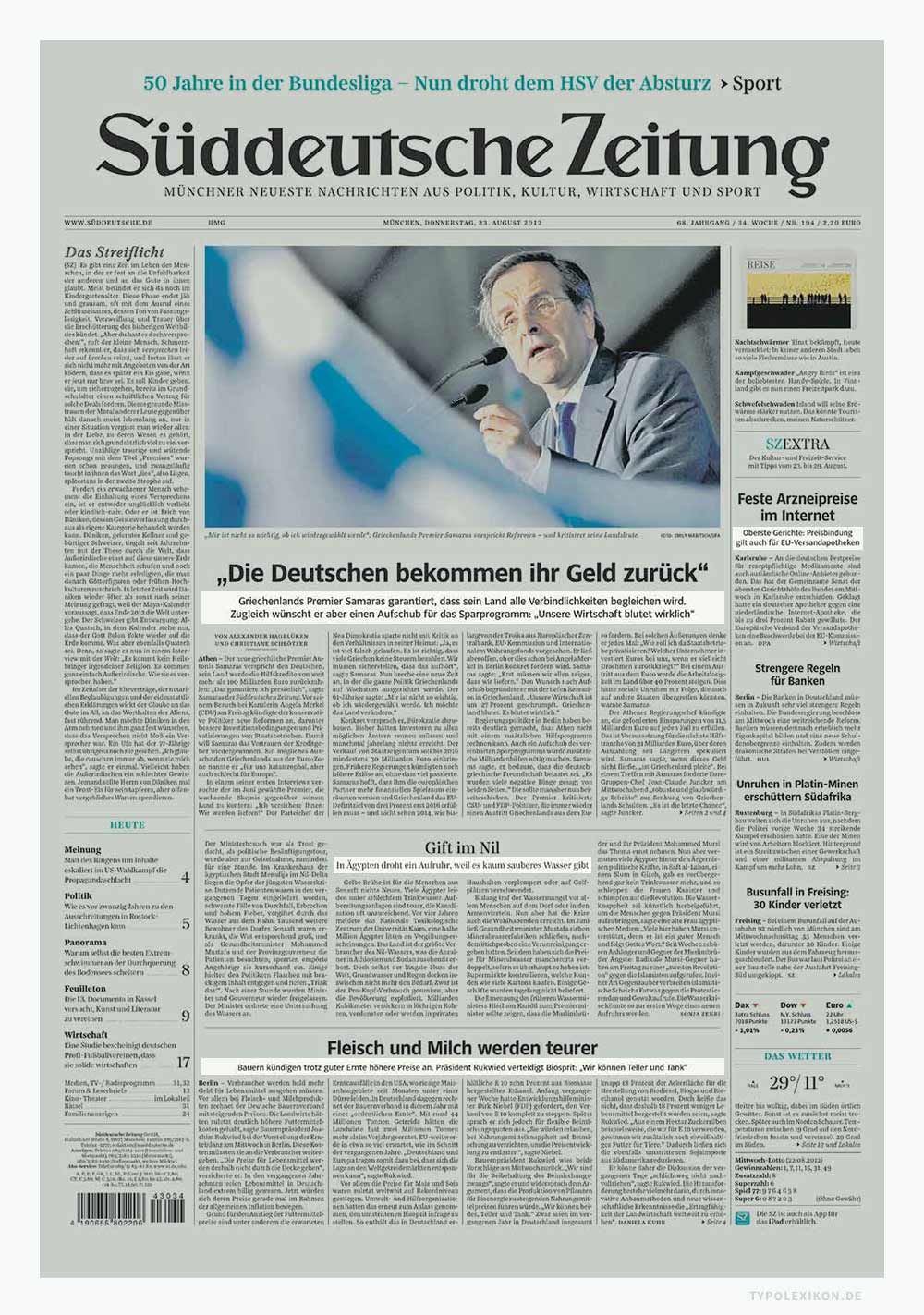
Die Schriftwahl für Sublines gehört in das Segment der Makrotypografie. Sublines zählen zur Integralen Schriftmischung und werden deshalb in einer semantisch-typografischen Auszeichnungsmatrix gegliedert und dokumentiert.
Webtypografie
In HTML/XHTML-Editoren (z.B. Adobe Dreamweaver®) oder Webanwendungen (z.B. WordPress® oder TYPO3®) können Headlines als Blockelemente hierarchisch in h1, h2, h3, h4, h5 und h6 (»h« steht für» heading«) gegliedert sowie semantisch zugeordnet und typografisch über »CSS Cascading Style Sheets« 2) ausgezeichnet werden, was sich nicht nur auf die Schriftsatzästhetik, sondern auch auf die »SEO Search Engine Optimization« (Suchmaschinenoptimierung) einer Website auswirken kann. I.d.R. wird für eine Subline das Element <h2> verwendet, was eine Überschrift zweiter Ordnung darstellt.
Beispiel von Headlines als Blockelemente in HTML:
<h1>1 Überschrift</h1> <h2>1.1 Überschrift</h2> <h3>1.1.1 Überschrift</h3> <h4>1.1.1.1 Überschrift</h4> <h5>1.1.1.1.1 Überschrift</h5> <h6>1.1.1.1.1.1 Überschrift</h6>
Etymologie und Herkunft
Etymologisch stammt das Präfix von eng. »sub« für »unter« von lat. »sub« für »unter, darunter« für deu. »unter, sich unterhalb befindend, niedriger als, darunter« und dem eng. Substantiv »line« für deu. »Linie, Zeile« zu eng. »Subline« für deu. »Unterzeile«.
Der dspr. Begriff »Unterzeile« ist deutlich älter als die espr. Bezeichnung Subline und stammt aus dem Akzidenzsatz der Zeitungsverlage.3) Der Terminus wurde spätestens mit der Entwicklung der Massenpresse im 19. Jahrhundert von der Englischen Typografie aus dem gewebespezifischen Sprachschatz der deutschen Zeitungstypografie als Lehnübersetzung übernommen. Der Begriff breitete sich dann mit der englischen Sprache als Weltsprache aus, explizit in die englischsprachige Welt, so auch in die Vereinigte Staaten von Amerika (USA).
Ab den 1920er Jahren wurde der Begriff Subline in den USA – insbesondere von der neuen Berufsgruppe der »Type Directors«, die in den neu gegründeten »Advertising Service Agencies« (Full Service Werbeagenturen) die Akzidenzsetzer verdrängten und später zu »Art Directors« wurden – aus dem Fachvokabular der Zeitungstypografie adaptiert.
Im deutschsprachigen Raum taucht der Anglizismus für Unterzeile in Anzeigen und Prospekten dann vermutlich erstmals in den 1950er Jahren mit den ersten deutschen Dependancen US-amerikanischer Werbeagenturen, z.B. McCann Erickson und J. Walter Thompson, im Frankfurter Raum (Hessen) auf.
Mit dem deutschen Wirtschaftswunder ab den 1950er Jahren und der damit verbundenen Prosperität des Wirtschaftsclusters »Kultur- und Kreativwirtschaft«, wurde der Anglizismus ab den 1970er Jahren sukzessive – so wie andere Anglizismen auch, bspw. die Begriffe Headline, Layout oder Copy – in Westdeutschland (BRD), Österreich und der deutschsprachigen Schweiz in die gängige Werbesprache bzw. in den gewebsspezifischen Sprachschatz übernommen.
| ↑1 | Anmerkung: Zwischentitel, Spitzmarken, Rubrikentitel oder Kolumnentitel sind keine Sublines. |
| ↑3 | Anmerkung: Die erste regelmäßige Tageszeitung der Welt – die »Einkommenden Zeitungen« des Typografen, Buchdruckers und Buchhändlers Timotheus Ritzsch (1614–1678) – kam am 1. Juli 1650 in Leipzig (Sachsen) heraus. |